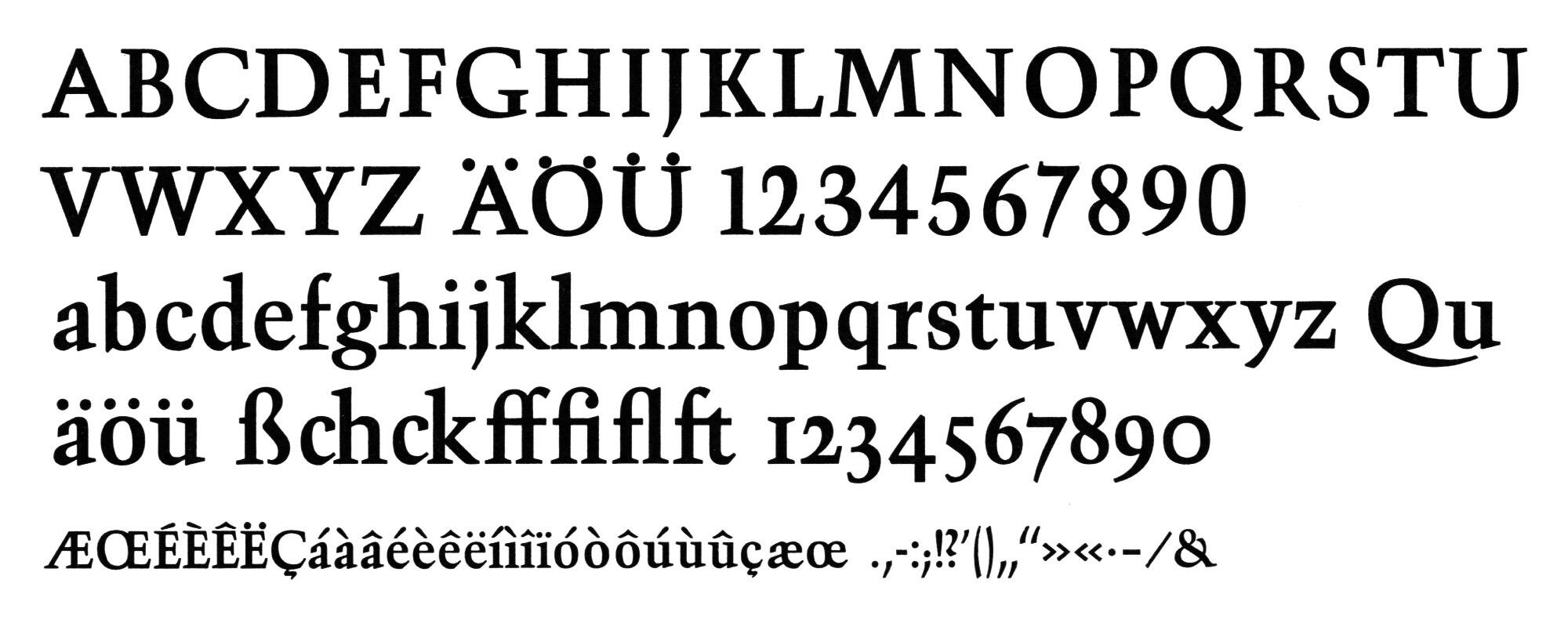
• circa 1954
• Serifen:
• serif
• Antiqua humanistisch
Die Trump-Mediäval gehört zu den bedeutendsten Schriftschöpfungen des deutschen Schriftgestalters Georg Trump. Nach dem Zweiten Weltkrieg waren die Frakturschriften im Zuge des Normalschrifterlasses nicht mehr gefragt und die Lücke füllten in den 1950er-Jahren neue Antiqua-Typen deutscher Schriftgestalter – etwa die allseits bekannte Palatino, aber auch die heute etwas in Vergessenheit geratene Trump-Mediäval, die 4 Jahre nach der Palatino bei C.E. Weber erschien.
Wie die Palatino musste sich die Mediäval den Satztechniken der Zeit unterwerfen und für Hand- und Maschinensatz (Linotype) gleichermaßen tauglichen sein. So hat auch die Trump-Mediäval im Normalschnitt und der Kursiven ein eher breit laufendes Antiqua-Skelett, jedoch kommt sie insbesondere in den Details verspielter und charakterstärker als Zapfs Palatino daher.
Der gute Ausbau der Familie in sieben Schnitten ermöglichte einen flexiblen Einsatz. Neben normal, kursiv, halbfett, fett und fettkursiv gab es auch einen schmalhalbfetten Schnitt sowie eine Gravur-Variante für den Schaueinsatz.